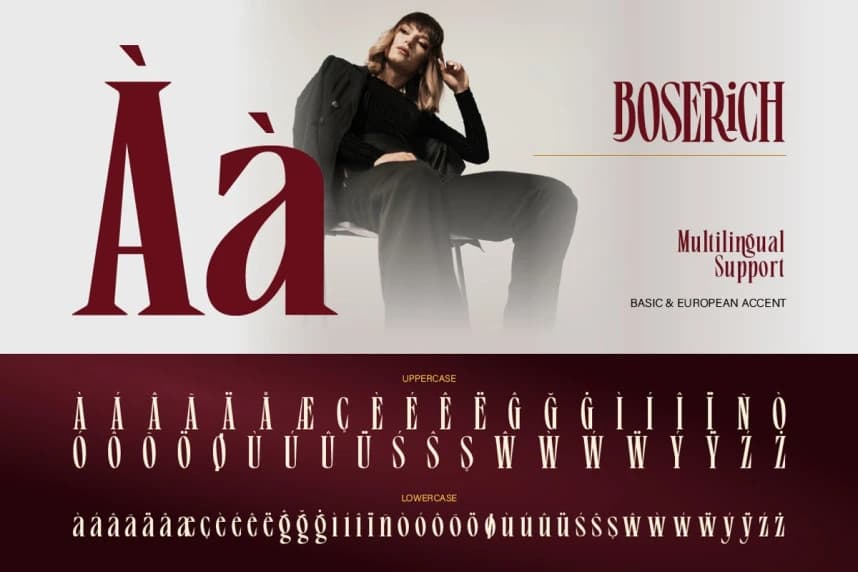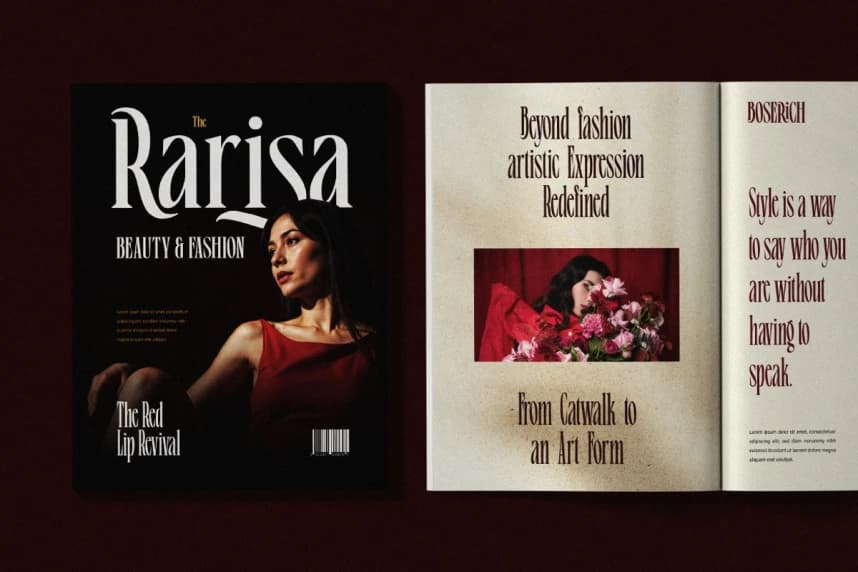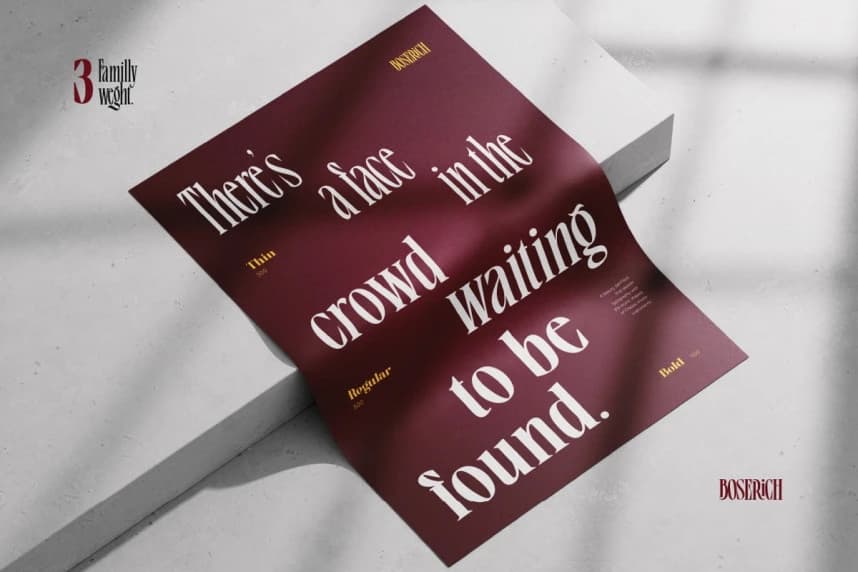
Boserich Font
Boserich Font, yaratıcı projelerinize lüks ve yüksek moda hissi kazandırmak için tasarlanmış modern ve zarif bir serif yazı tipidir. Editoryal dergilerden, lüks markalaşmadan ve çağdaş moda estetiğinden ilham alınmıştır.
Boserich Font, yaratıcı projelerinize lüks ve yüksek moda hissi katması için tasarlanmış modern zarif bir serif yazı tipidir. Editoryal dergilerden, lüks markalaşmadan ve çağdaş moda estetiğinden ilham alınmıştır.